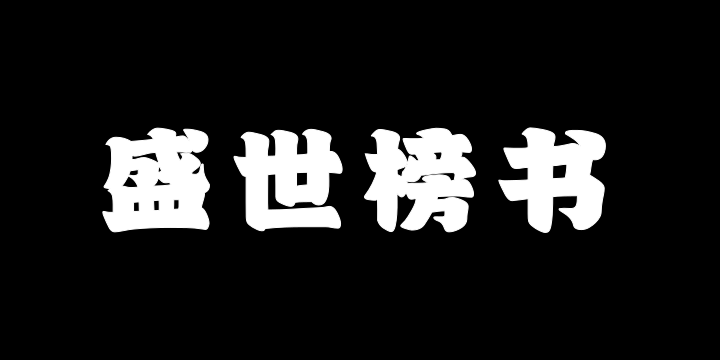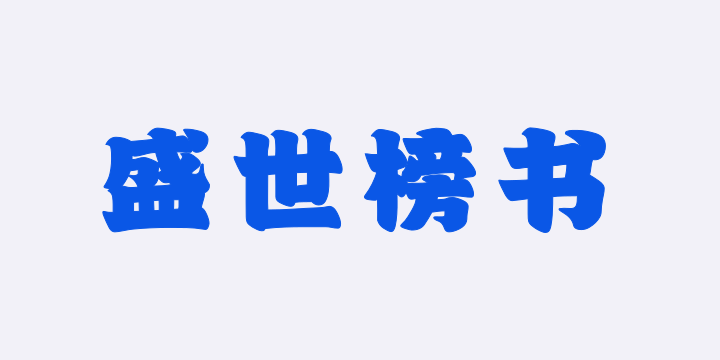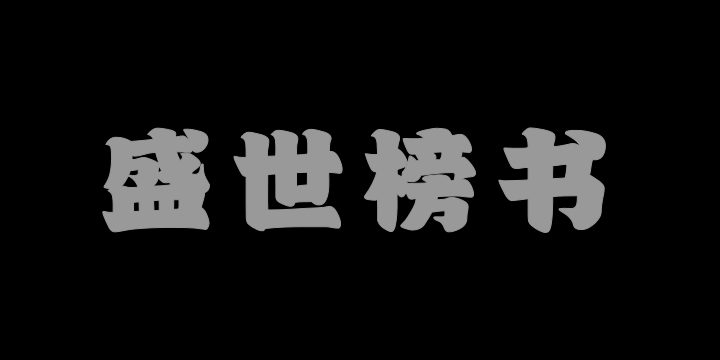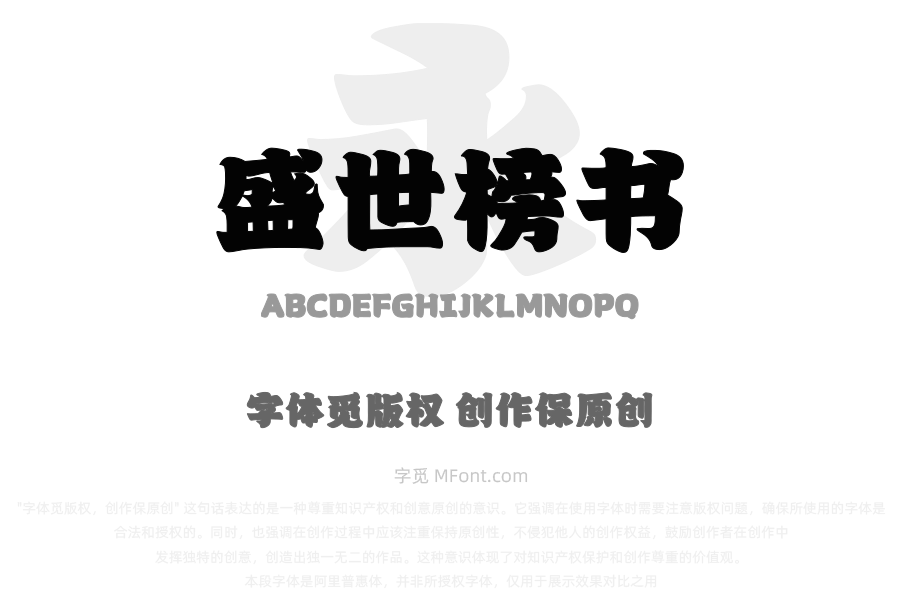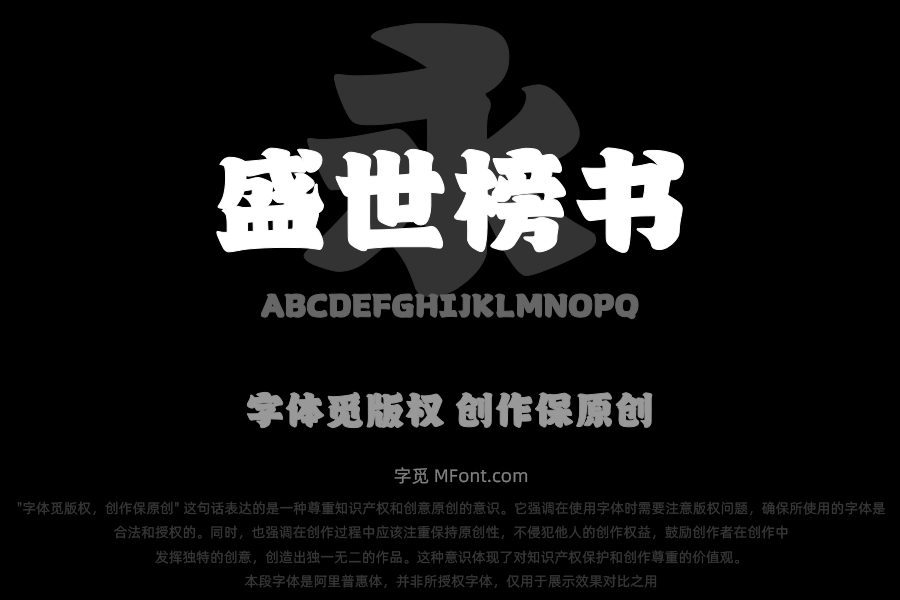
关于山海盛世榜书W字体字库信息
字体全名: 山海盛世榜书W
铸字厂: 山海字库
设计师: 山海字库
字体简介: 山海盛世榜书,是一款擘窠大字榜书字体。包含简繁汉字9169个。该字体雄健有力,霸气外露,在粗细的纵横间,拥有非常规的张力特性。该字体的笔画充满力量感,组合搭配极富强烈的节奏感,融入楷书特点,使字体的视觉效果有力、宽厚、方正,充满了稳重感和设计感。笔画与字形间透露着榜书的古雅和刚劲的特点,在浑厚的同时而又极富张力,桀骜不驯的特性,霸气外露。